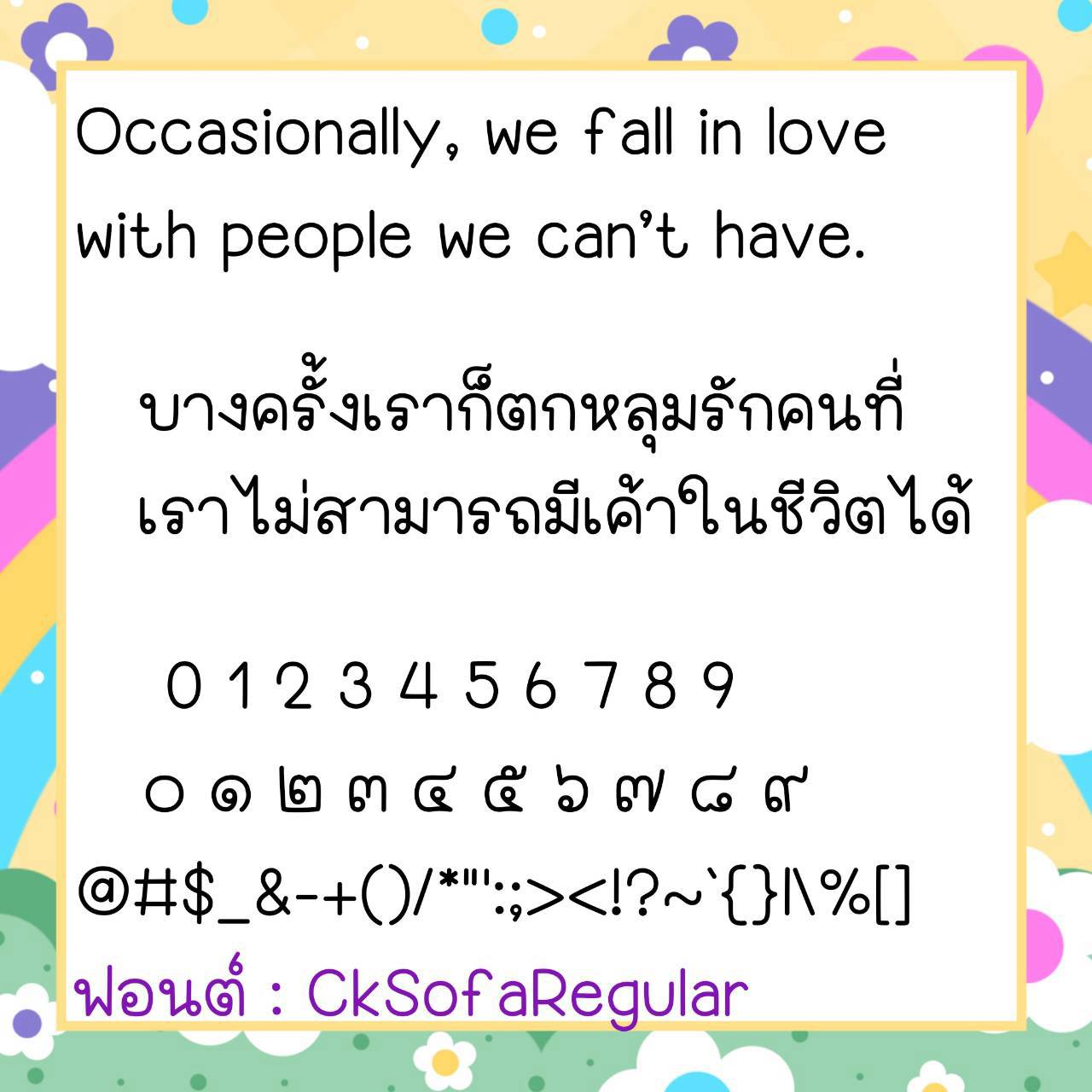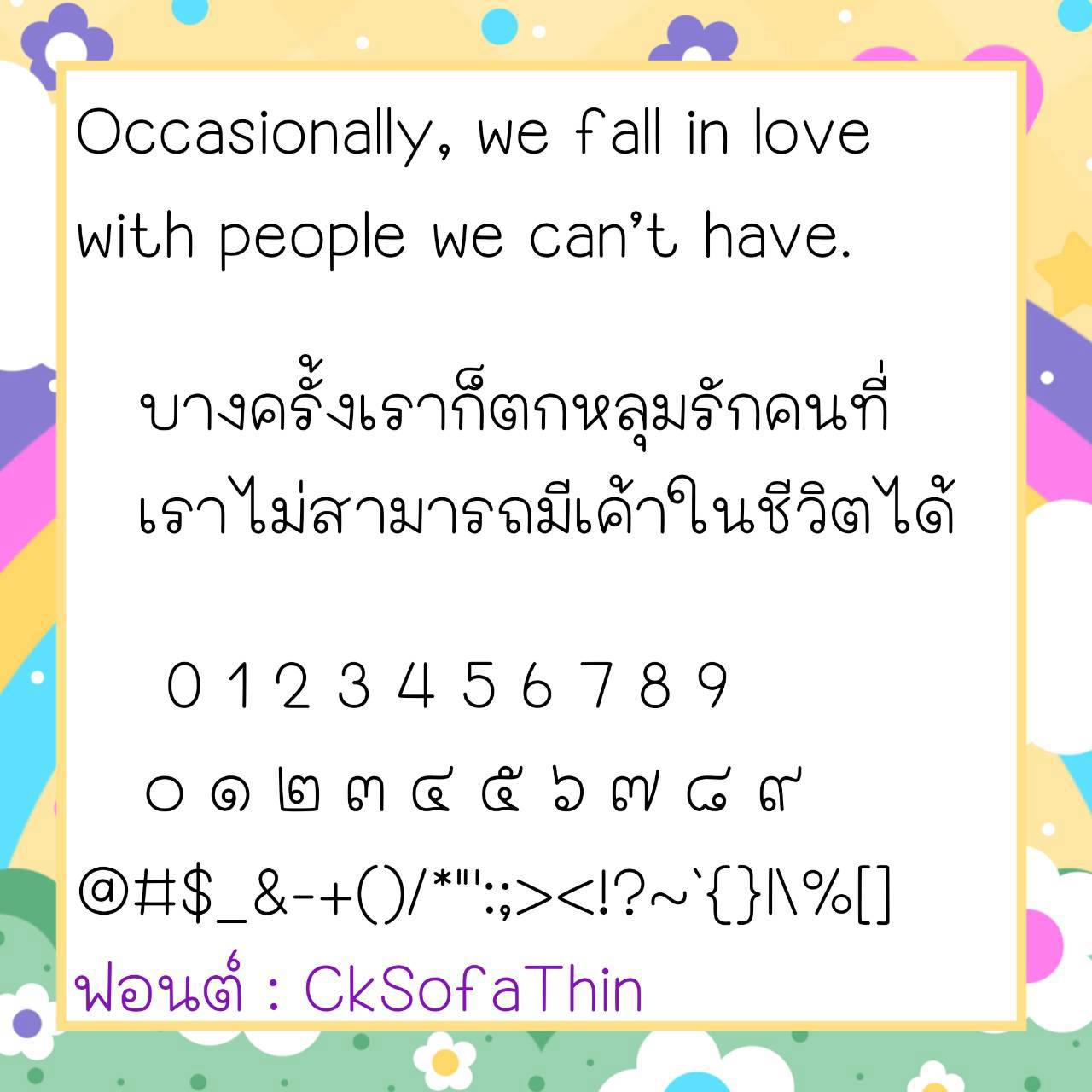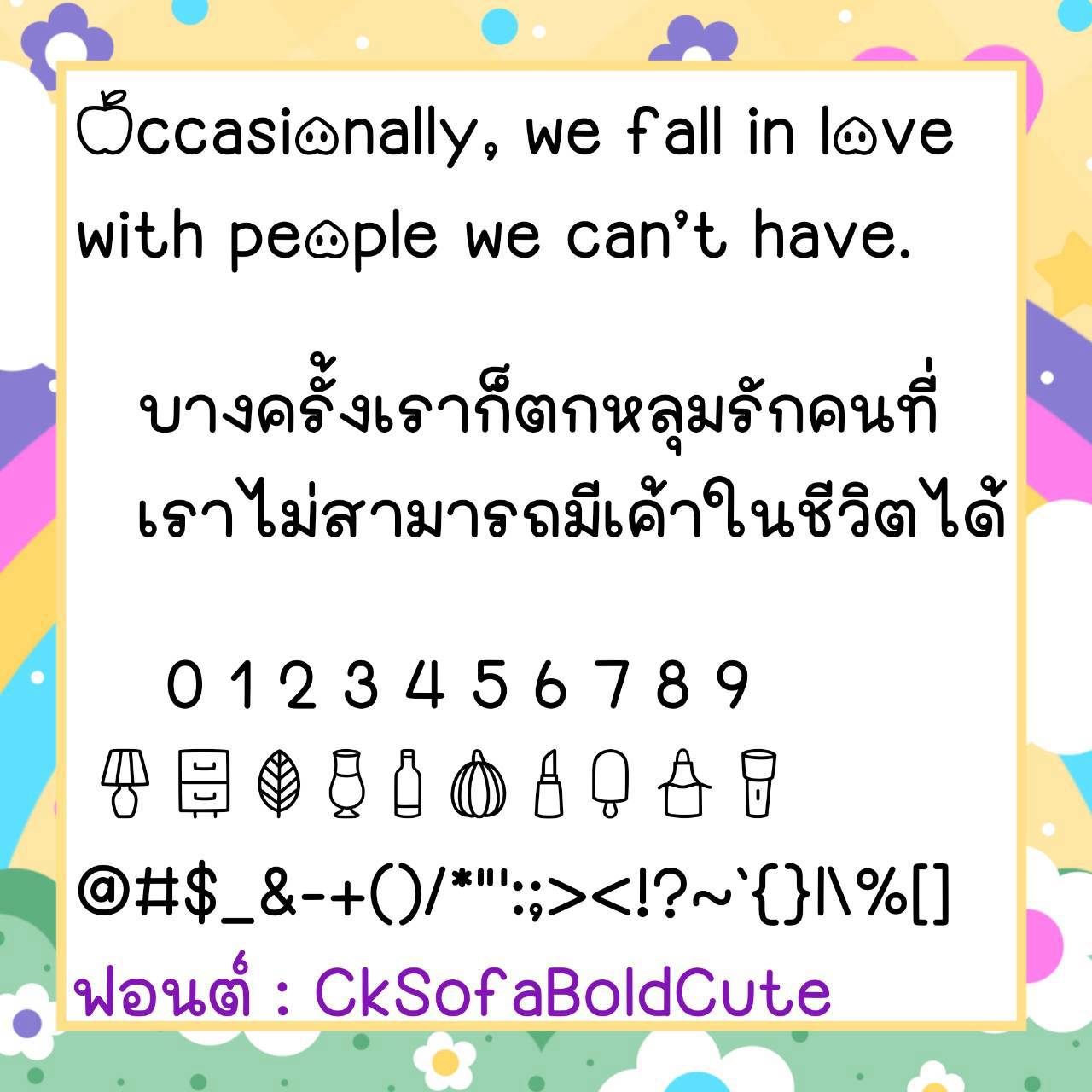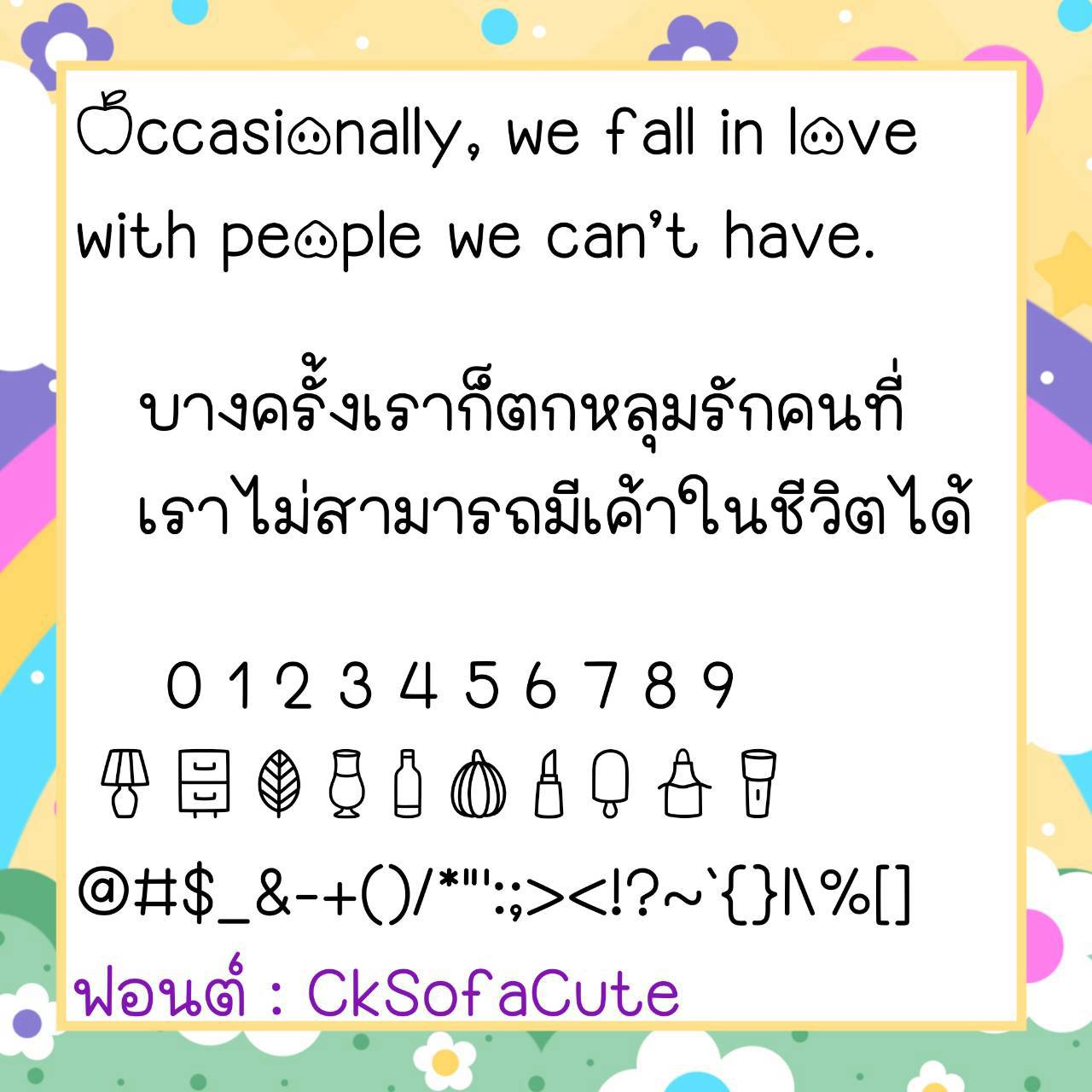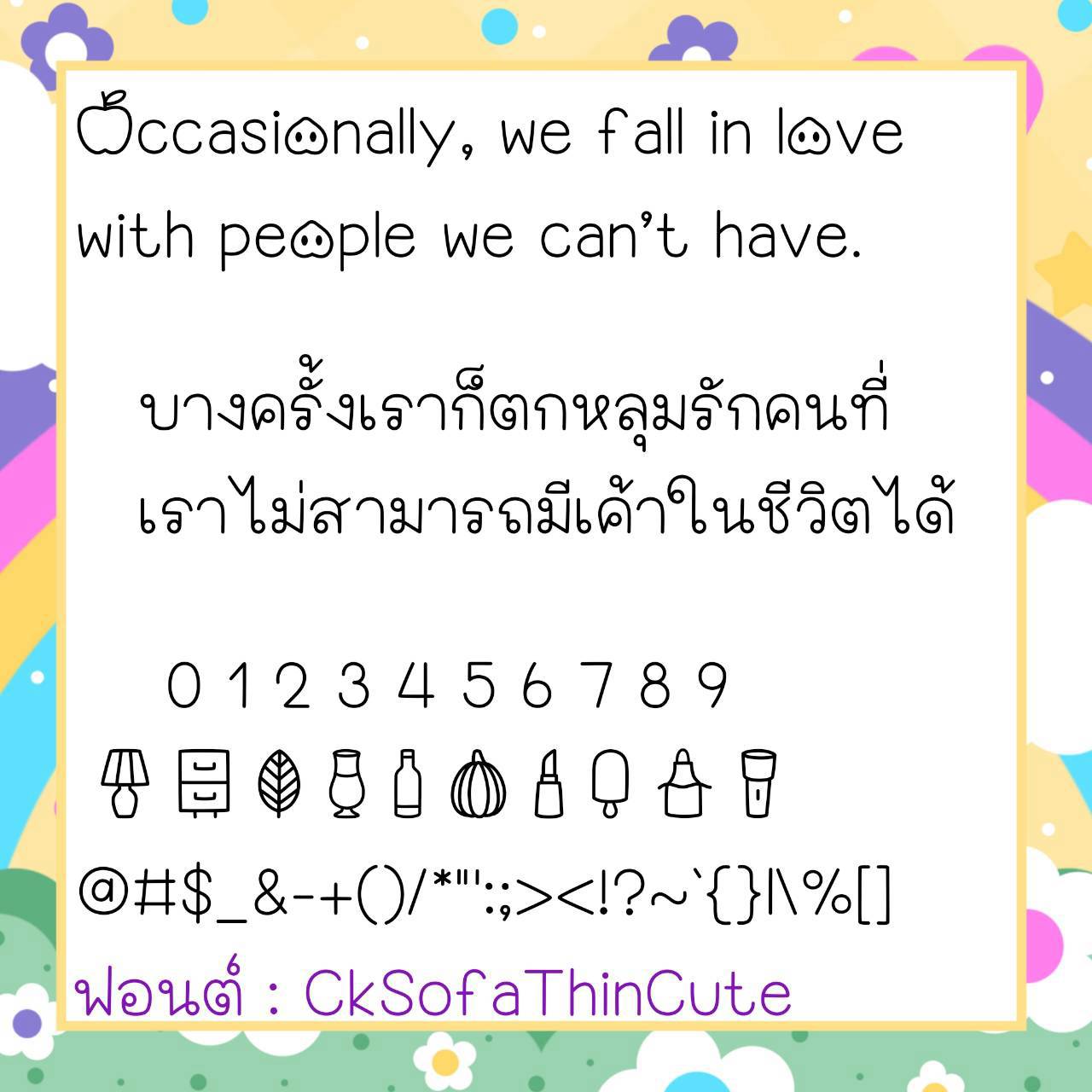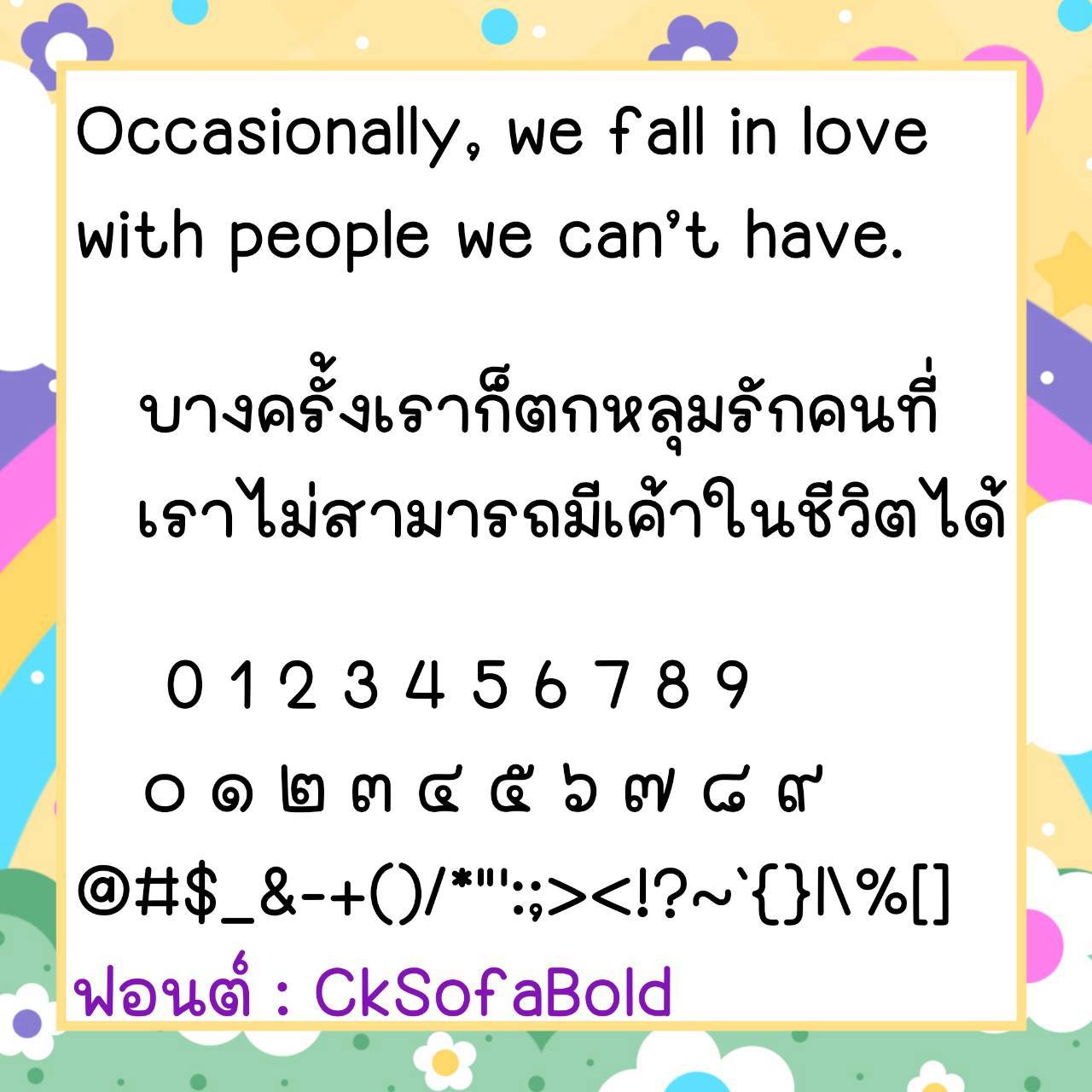
Font CkSofa
🔸 ฟอนต์ลายมือแนวน่ารักแบบวัยรุ่น ตัวอ้วนกลม ใช้งานง่ายใช้ได้หลากหลาย อ่านง่ายสบายตา และยังมีไฟล์อิโมจิน่ารักๆที่ใช้แทนเลขไทยให้ด้วยค่ะ 🥰💙
🔹 A cute, youthful handwritten font with chubby, round characters. It’s easy to use, versatile, and easy on the eyes. It also includes cute emoji files to replace Thai numerals. 🥰💙